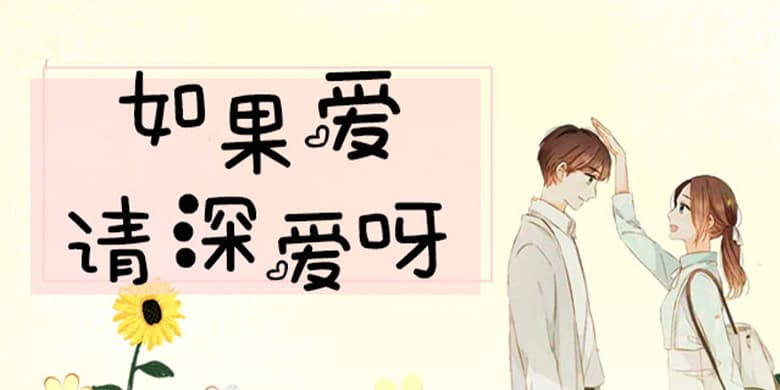
品牌:方正手迹设计师:俞亦婷发行时间:2019字库编码:大陆简体(GB2312-80)分类:创意书写字体属性:精品字
如果爱请深爱呀体,这款字体字形部首打破传统规律,将部件或夸张放大或缩小变形,使得每个字都与众不同,点画巧妙处理成实心圆点点缀其中更添趣味。适用于青少儿类的书刊、综艺字幕、品牌广告和产品包装设计,以及社交网络的个性化用字。